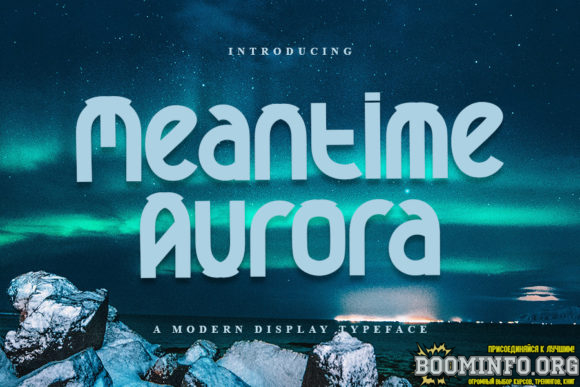
Creativefabrica Meantime Aurora Font
[Creativefabrica] Meantime Aurora Font
Meantime Aurora - это смелый и современный шрифт.
Это идеальный шрифт для создания оригинальных и выдающихся дизайнов.